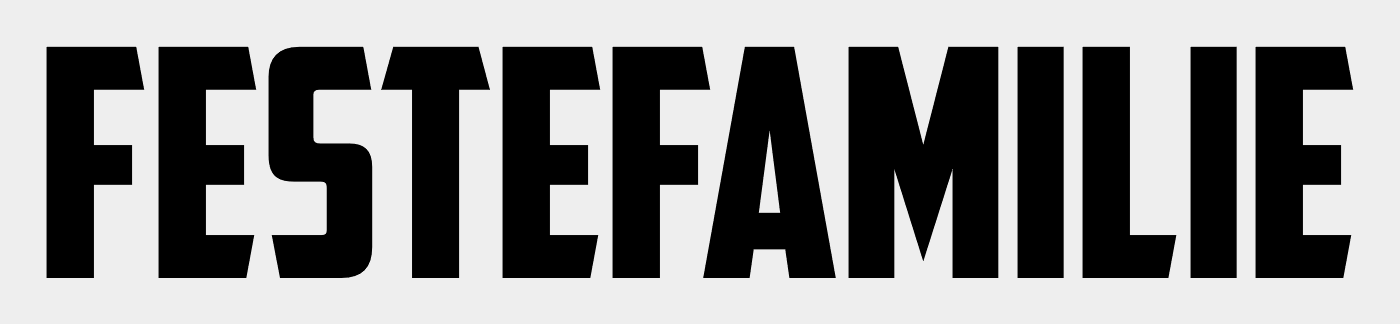
Schriftart gesucht (Familienfest)
ich habe auf einem Plakat die folgende Schriftart gesehen und war zuerst zur Super Grotesk hingezogen. Das abgeschrägte E und das spitz zulaufende M waren der Grund. Dem entgegen aber steht das ungewöhnliche S. Wer kann helfen, um welche Schriftart es sich handelt?